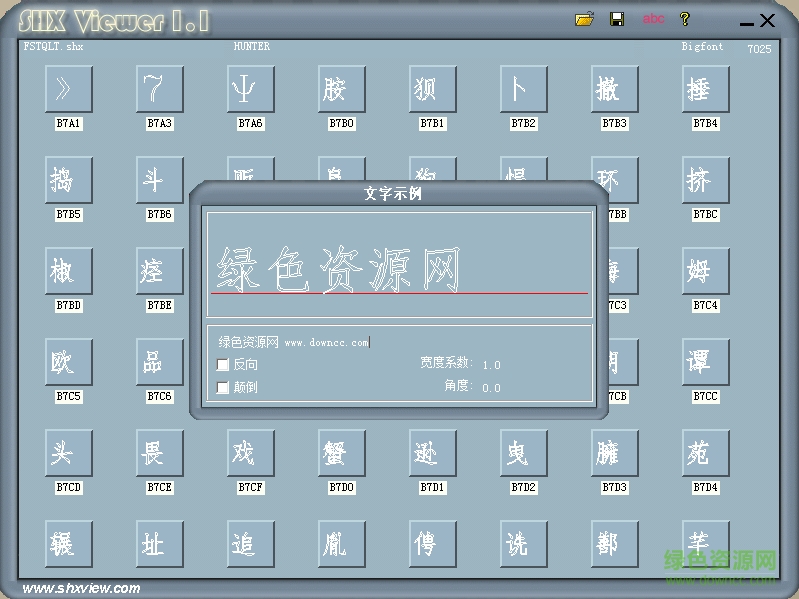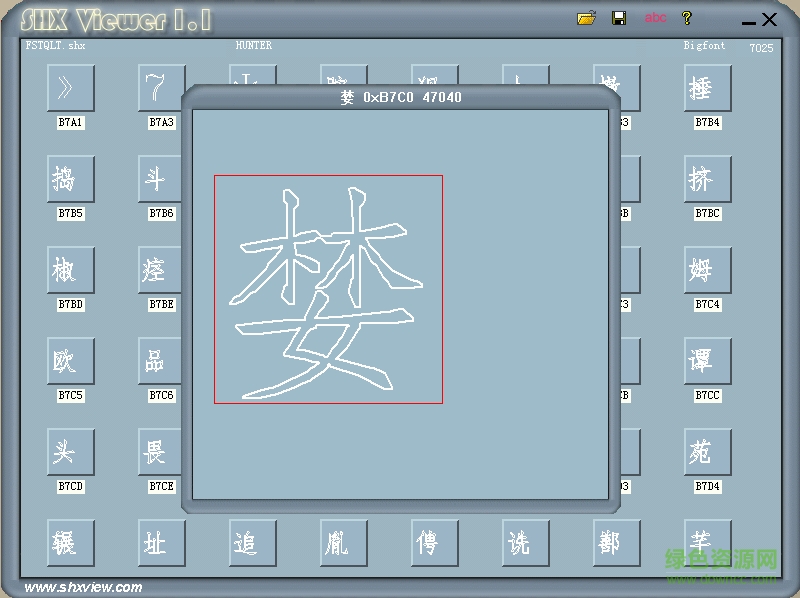
fstqlt.shx(橋梁字體)
fstqlt.shx是一款空心cad字體,以楷體書(shū)法為模板,字跡平直端正,行筆處抑揚(yáng)頓挫,很有藝術(shù)美感,喜歡的朋友不妨來(lái)綠色資源網(wǎng)免費(fèi)下載體驗(yàn)!
fstqlt字體簡(jiǎn)介
fstqlt.shx是autocad中的bigfont,選用楷體的精髓,空心結(jié)構(gòu)讓字體顯得立體生動(dòng),擁有70265個(gè)字符,包括漢字、數(shù)字和部分符號(hào)等,滿(mǎn)足平面設(shè)計(jì)中的常用要求。
fstqlt.shx字體
楷體字體特色
楷書(shū)的特點(diǎn)主要有以下三個(gè)方面:
①起止三折筆,運(yùn)筆在中鋒,是楷書(shū)的典型筆法。古人說(shuō)"真多用折,……折欲少駐,駐則有力。"運(yùn)筆中鋒則多遒潤(rùn)。
②筆劃有規(guī)律的發(fā)展,形成了"永字八法"。它既是字法,也是筆法。一切楷書(shū)的筆劃,都概括于八法之中。每一點(diǎn)劃都不是孤立的,而是和其他筆劃互相呼應(yīng)的。永字的八個(gè)筆劃按其所處位置各有名稱(chēng),不再贅述。
③筆劃平正,結(jié)體整齊,工妙于點(diǎn)畫(huà),神韻于結(jié)體。平正而不呆,齊整而不拘。古人說(shuō),"楷法欲如快馬入陣","大字難于結(jié)密而無(wú)間,小字難于寬綽而有余。"要的是嚴(yán)整飄揚(yáng)、犀利飛動(dòng)。